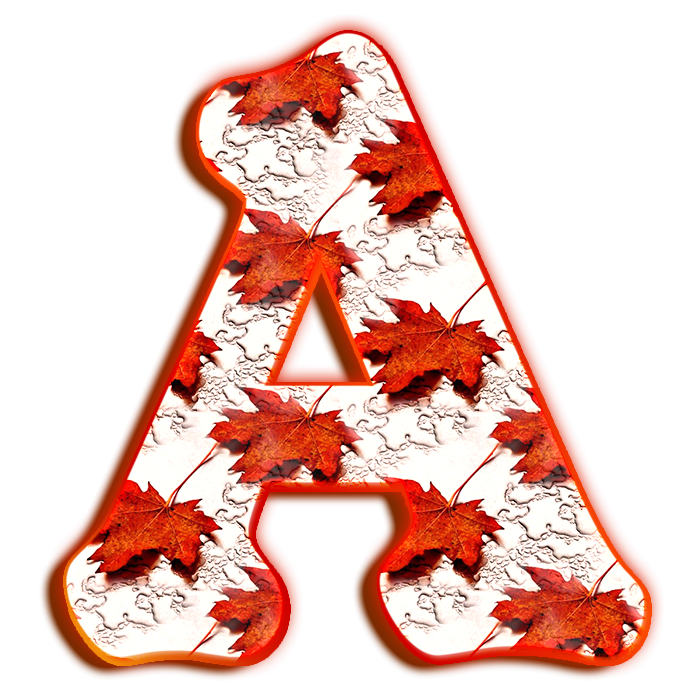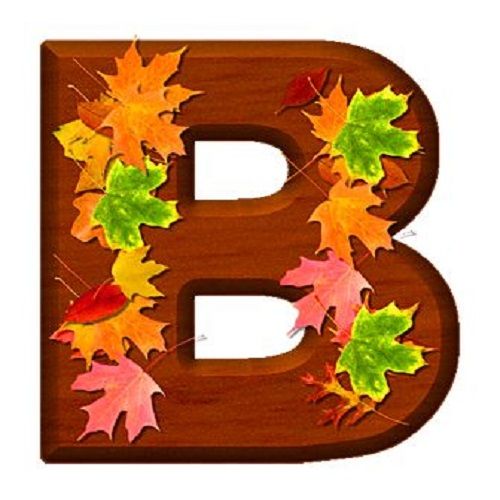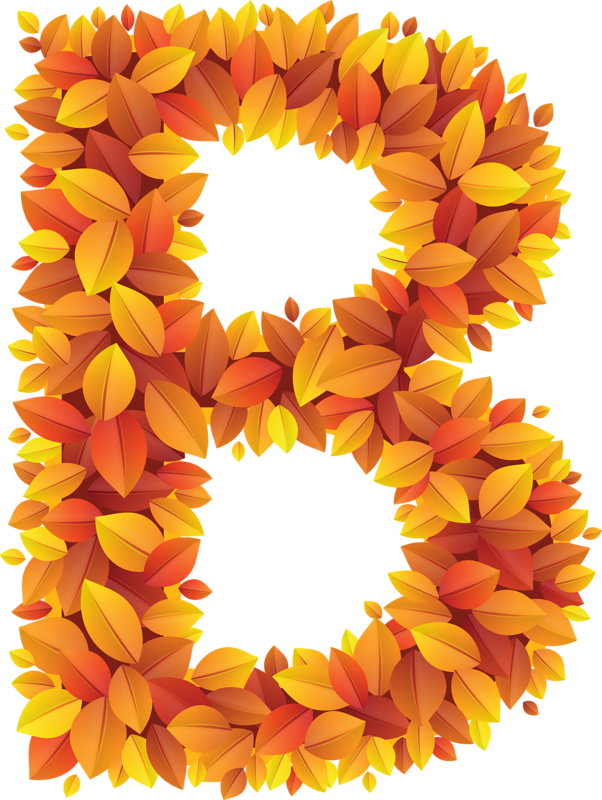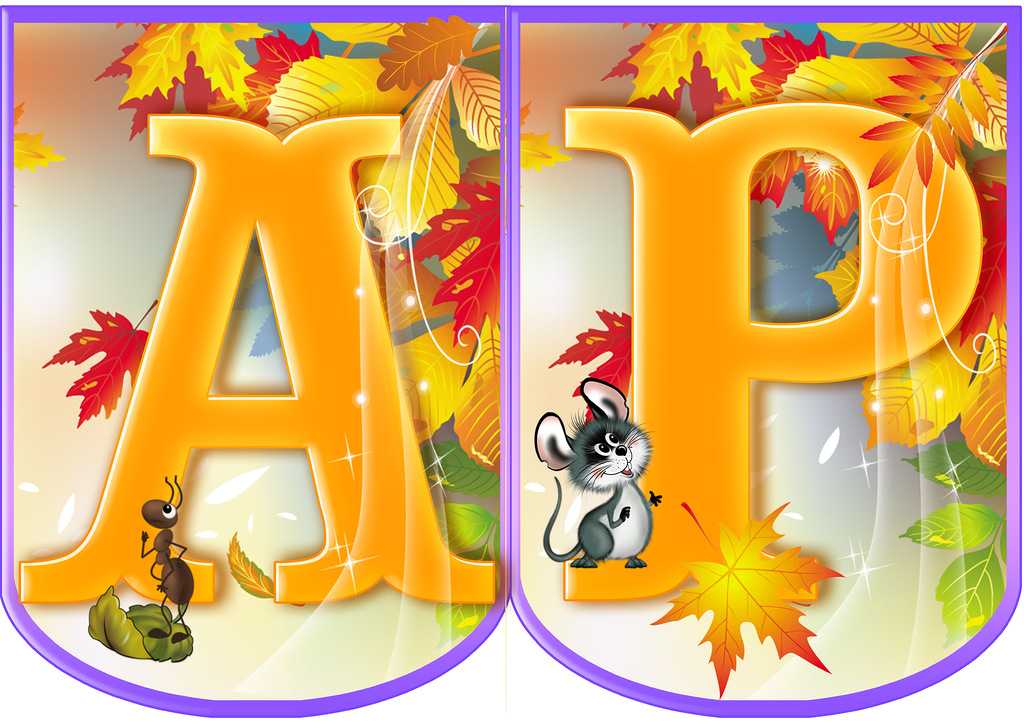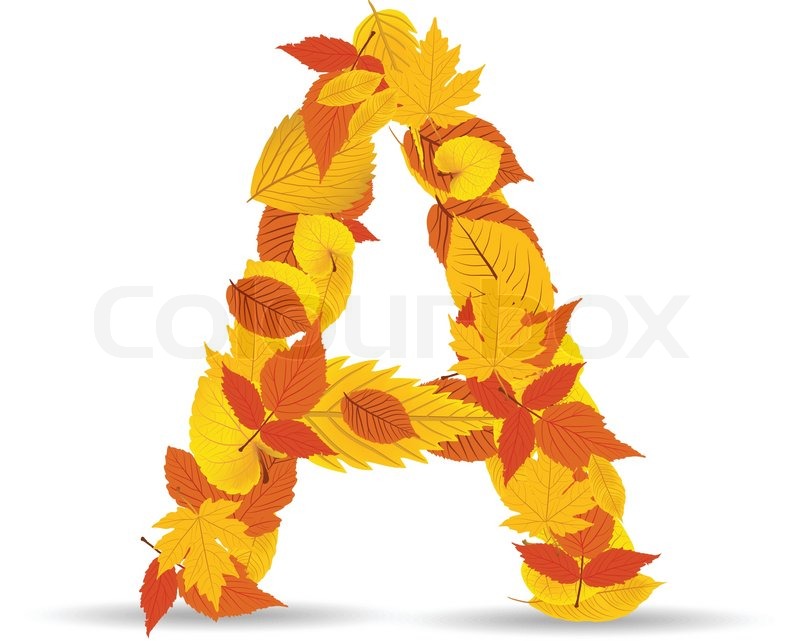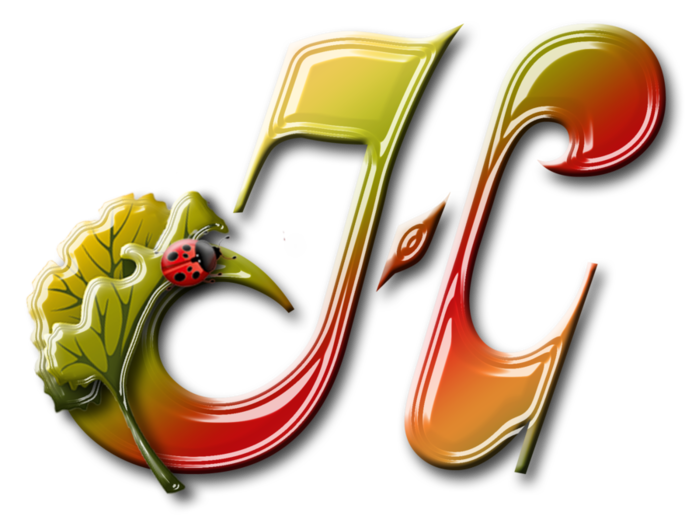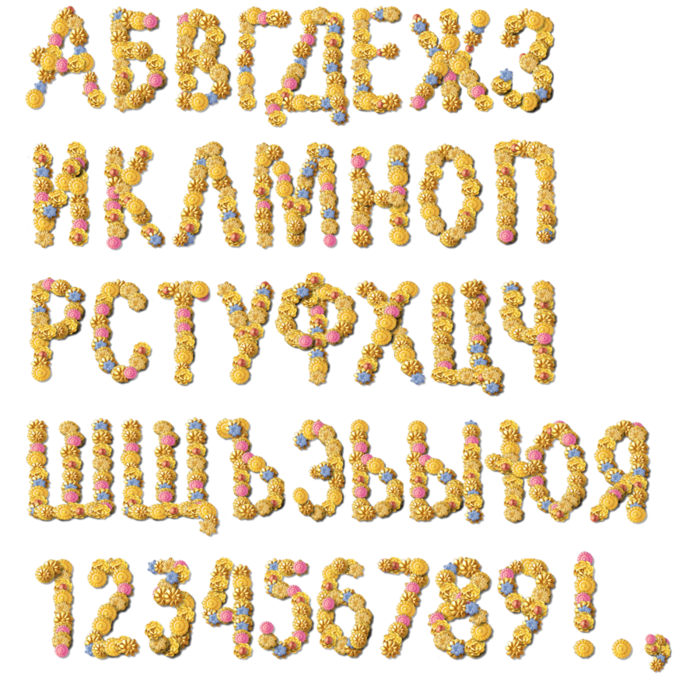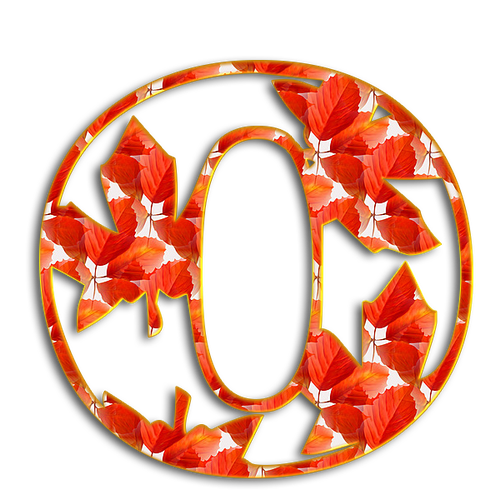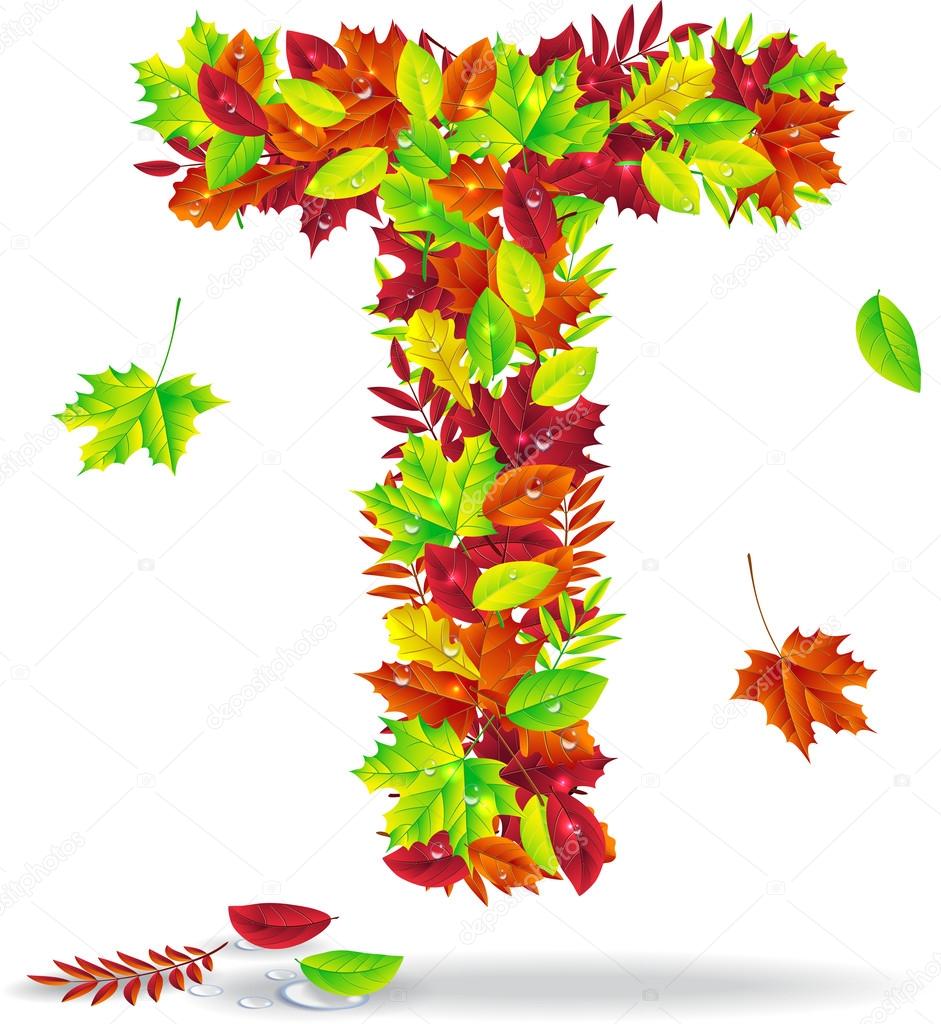
Осенний русский шрифт: 16 лучших бесплатных осенних и осенних шрифтов
16 лучших бесплатных осенних и осенних шрифтов
Эта коллекция бесплатных осенних шрифтов вызовет в воображении образы тыквенных пятен , уютных свитеров, дымящихся чашек яблочного сидра, хрустящих листьев под ногами и золотых рассветов.
Эти бесплатные осенние шрифты могут быть использованы для ваших онлайн или печатных проектов. Это хорошая комбинация изящных шрифтов сценариев с более смелыми преднамеренными шрифтами. Вы должны быть в состоянии найти шрифт, который вам нравится, независимо от того, для чего вы хотите его использовать.
Вам понравится этот бесплатный осенний шрифт Cinnamon Cake, который действительно превратит ваш текст в нечто особенное.
Homegirl Harvest — это шрифт, который соответствует своему названию. Это немного кантри и немного женственно, все в одном лице. Это идеальный шрифт для всего, что связано с тыквой.
Шрифт Morning Coffee заставляет меня думать о теплых кружках кофе, какао и сидра, с паром, кружащимся над ними.
Бесплатный осенний шрифт Great Vibes обладает большей элегантностью, чем другие шрифты, которые я здесь представил. Я действительно могу изобразить это на карточках на столе Благодарения или в сердечном письме любимому человеку.
Marydale — это рукописный шрифт, который напоминает мне о долгих прогулках в оживленный осенний день с хрустящими листьями под ногами.
Apple Butter — это бесплатный шрифт, который отлично подойдет, если вы хотите, чтобы ваш текст выглядел винтажно, но все еще сезонно. Я думаю, что этот шрифт будет отлично смотреться на консервы и рецепты.
Этот шрифт с соответствующим названием, «Осень», представляет собой извилистый, но жирный шрифт для рукописного ввода, который, как я вижу, используется для любого онлайн или печатного проекта.
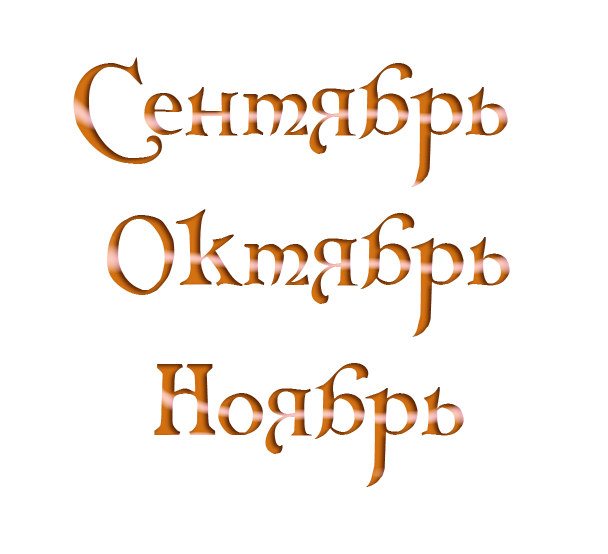
Pea Pumpkin Peters — это шрифт, который идеально подходит для осеннего времени. Этот шрифт легко читается, но он все еще веселый и приятный.
«День осени» — это тонкий шрифт, который создает впечатление, что осенние листья не падают сверху. Это довольно шепот шрифта, который обязательно произведет впечатление.
Appleberry — это смелый осенний шрифт, который представляет собой идеальное сочетание современного и старомодного. Знаки, баннеры, информационные бюллетени и множество других проектов будут отлично смотреться с этим шрифтом.
Cutie Patootie — бесплатный осенний шрифт, который представляет собой идеальное сочетание веселья и изысканности.
Этот шрифт отлично подойдет для любого текста, который будет отображаться в октябре или ноябре.
Помимо версии, которую вы видите здесь, этот осенний шрифт также доступен в полых и узких версиях.
Acryle Script — это смелый сценарий, в котором есть тонна процветания и отношения. Этот шрифт свободного падения требует внимания и вызывает прекрасное чувство счастья и удовлетворения.
Always In My Heart — это очень красивый рукописный шрифт, который заставляет меня думать о золотых рассветах, теплых свитерах и держаться за руки.
Обязательно ознакомьтесь с числами этого шрифта, они очень хороши и будут отлично смотреться практически на чем угодно.